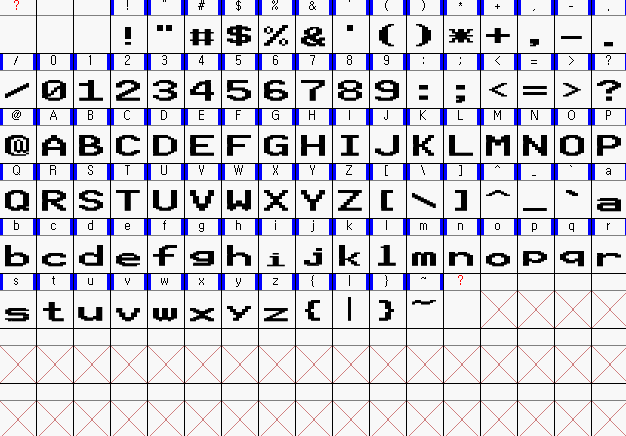
bitMatrix-E1-wide
bitMatrix-E1 family fonts are often used by some banks to print the POS receipts. Sometimes they are used for Australia GM Cabs taxi receipts.
Contoh hasil cetak 1 (①bitMatrix-E1-wide ②bitMatrix-E1):
Contoh hasil cetak 2 (KBank) (①bitMatrix-E1-wide):
Contoh hasil cetak 3 (①bitMatrix-E1-wide):
Contoh hasil cetak 4 (①bitMatrix-E1-wide):
Contoh hasil cetak 5 – Australia GM Cabs taxi receipt (①bitMatrix-E1-wide ②bitMatrix-E1):
Contoh hasil cetak 6 – Australia GM Cabs taxi receipt (①bitMatrix-E1-wide ②bitMatrix-E1):
Contoh hasil cetak 7 — struk taksi GM Cabs Australia:
Contoh hasil cetak 8 – Australia GM Cabs taxi receipt (①bitMatrix-E1-wide ②bitMatrix-E1):
Contoh hasil cetak 9 — struk taksi GM Cabs Australia:
Contoh hasil cetak 10 – Australia GM Cabs taxi receipt (①bitMatrix-E1 ②bitMatrix-E1-wide):
Semua karakter font bitMatrix-E1-wide:
Font bitMatrix-E1-wide dilihat dengan penampil font bawaan Windows: